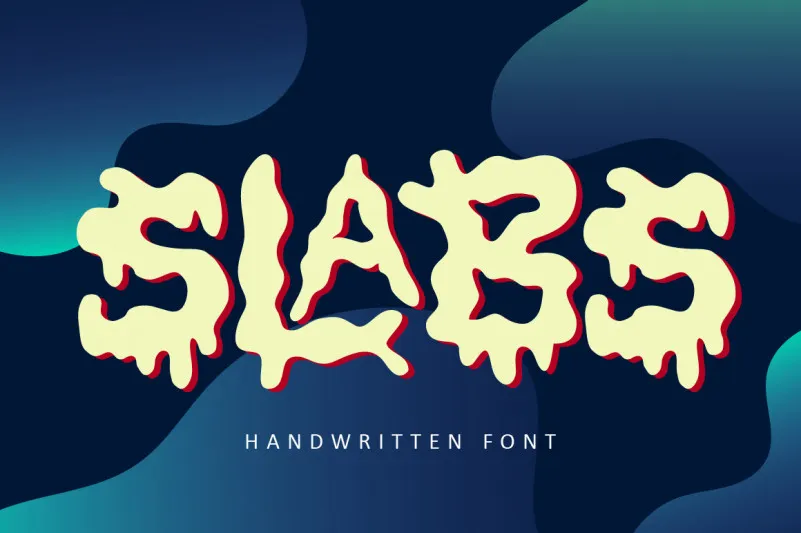
Slabs – Fun Font é uma elegante fonte Serif Largada que ganha vida com seu estilo robusto e abstracto. Esta fonte foi criada com influências de escrita a mão, tornando-a perfeita para uma variedade de projetos de design. Seja você um designer de revistas, criação de roupas, arte manual ou até mesmo para criar marcas de produtos, Slabs – Fun Font será o elemento ideal para dar aos seus trabalhos aquela personalidade única e divertida que tanto deseja. Ideal tanto para letras como para logotipos, esta fonte é uma escolha atraente e confiável para qualquer projeto visual.